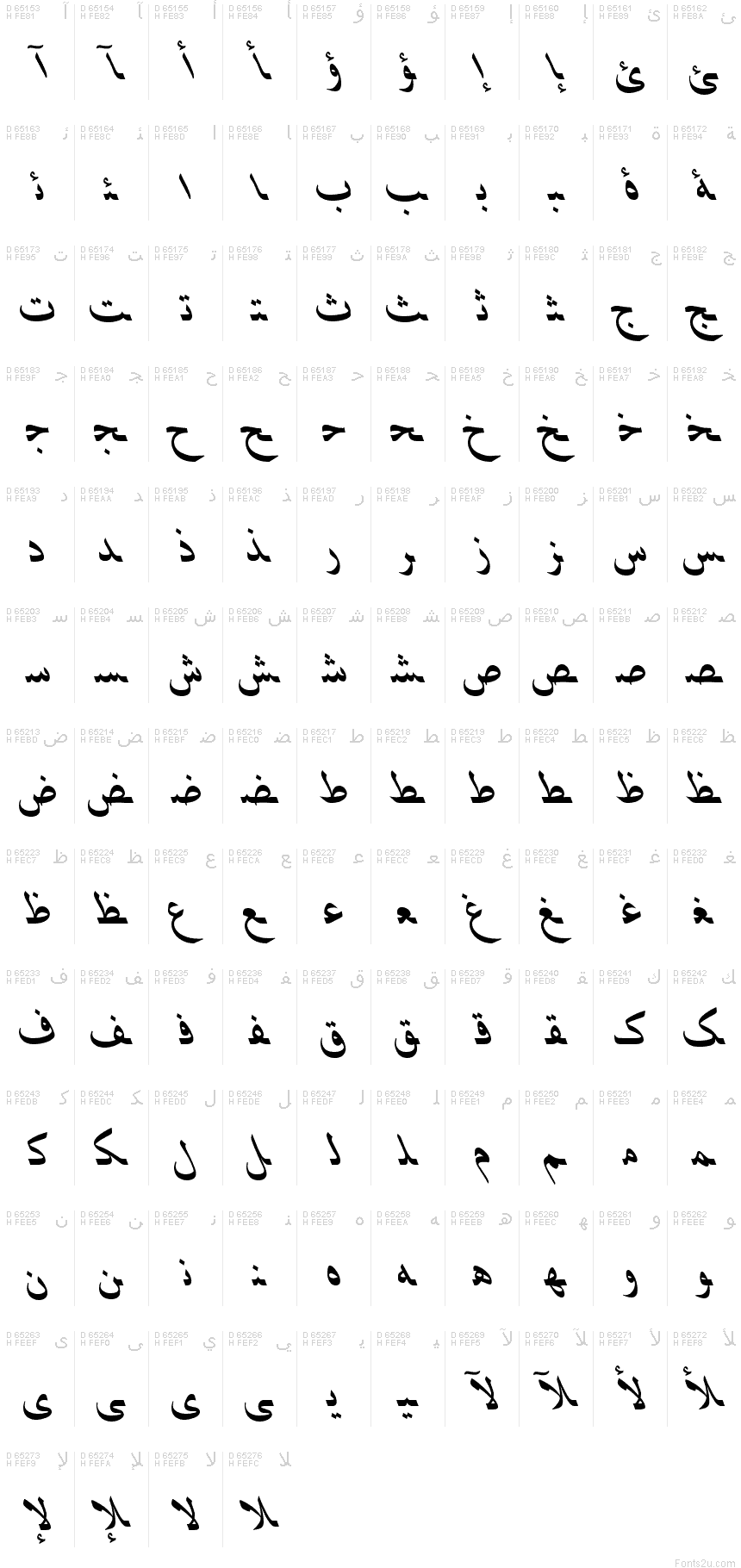
B Shiraz Italic von Borna Rayaneh ist eine kostenlose arabische Kalligrafie-Schrift, die das fließende, dynamische Gefühl von Nastaliq-inspirierten Buchstaben einfängt. Die Striche neigen sich nach vorne und laufen in scharfen, lebendigen Verbindungen aus, während der Gesamteindruck ein Auf und Ab erzeugt, das sich eher handschriftlich anfühlt als starr gesetzt.
Sie eignet sich ideal für persische und arabische Buchcover, kulturelle Plakate, Lyriktitel, Verpackungen und redaktionelle Überschriften, bei denen das Schriftbild selbst Stimmung vermittelt. Als kostenlose Schrift funktioniert sie am besten in kurzen Zeilen, Titelkarten und markanten Signaturen, wo die schwungvolle, kursive Bewegung im Vordergrund steht.
Zeichentabelle der Schriftart B Shiraz Italic
Zeichentabelle von B Shiraz Italic: Arabische Präsentationsformen-B, Seite 1
Glyphen der Schriftart B Shiraz Italic — Arabische Präsentationsformen-B, Seite 1